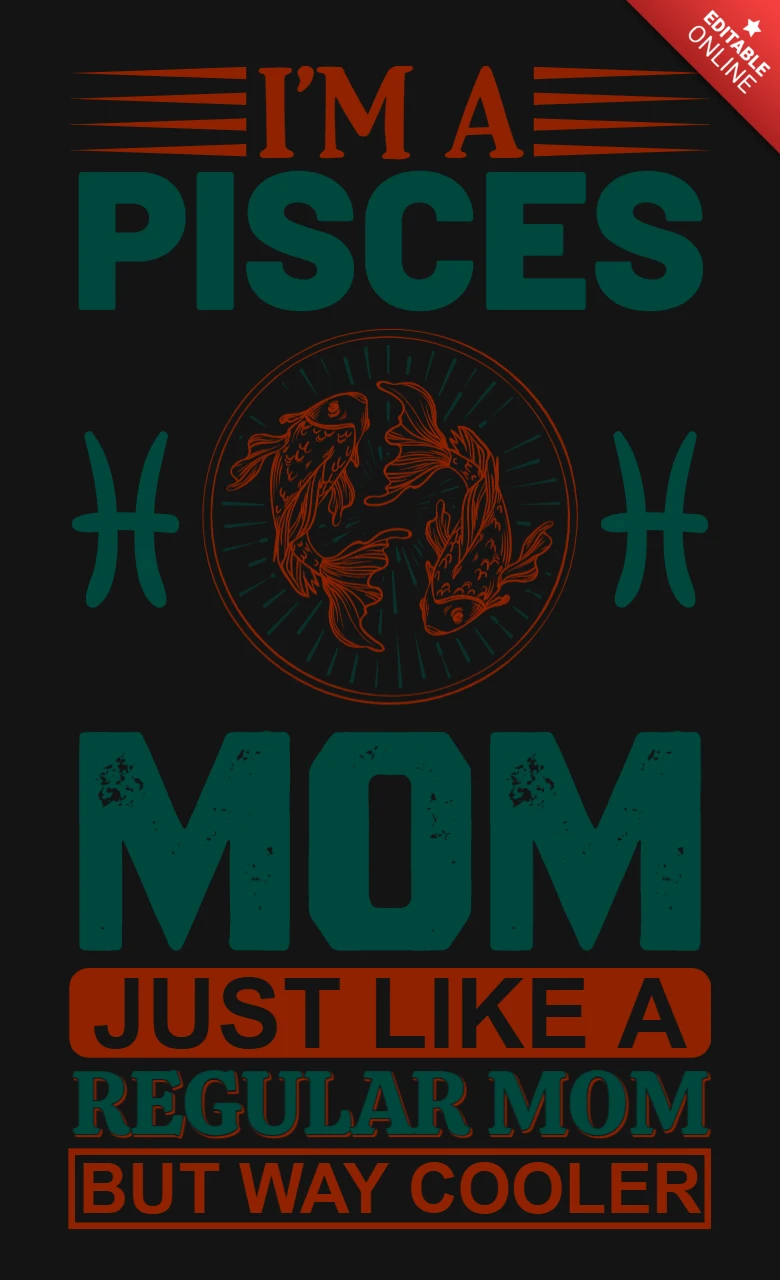
Vissen mama retro typografie ontwerpsjabloon voor aangepaste kleding
Bewerken in Design Studio Downloaden in JPGMaak het perfecte verjaardagscadeau met onze ontwerpsjabloon met retro Vissen-thema, met humoristische citaten en stijlvolle typografie - ideaal voor kleding die het astrologische teken van mama viert!